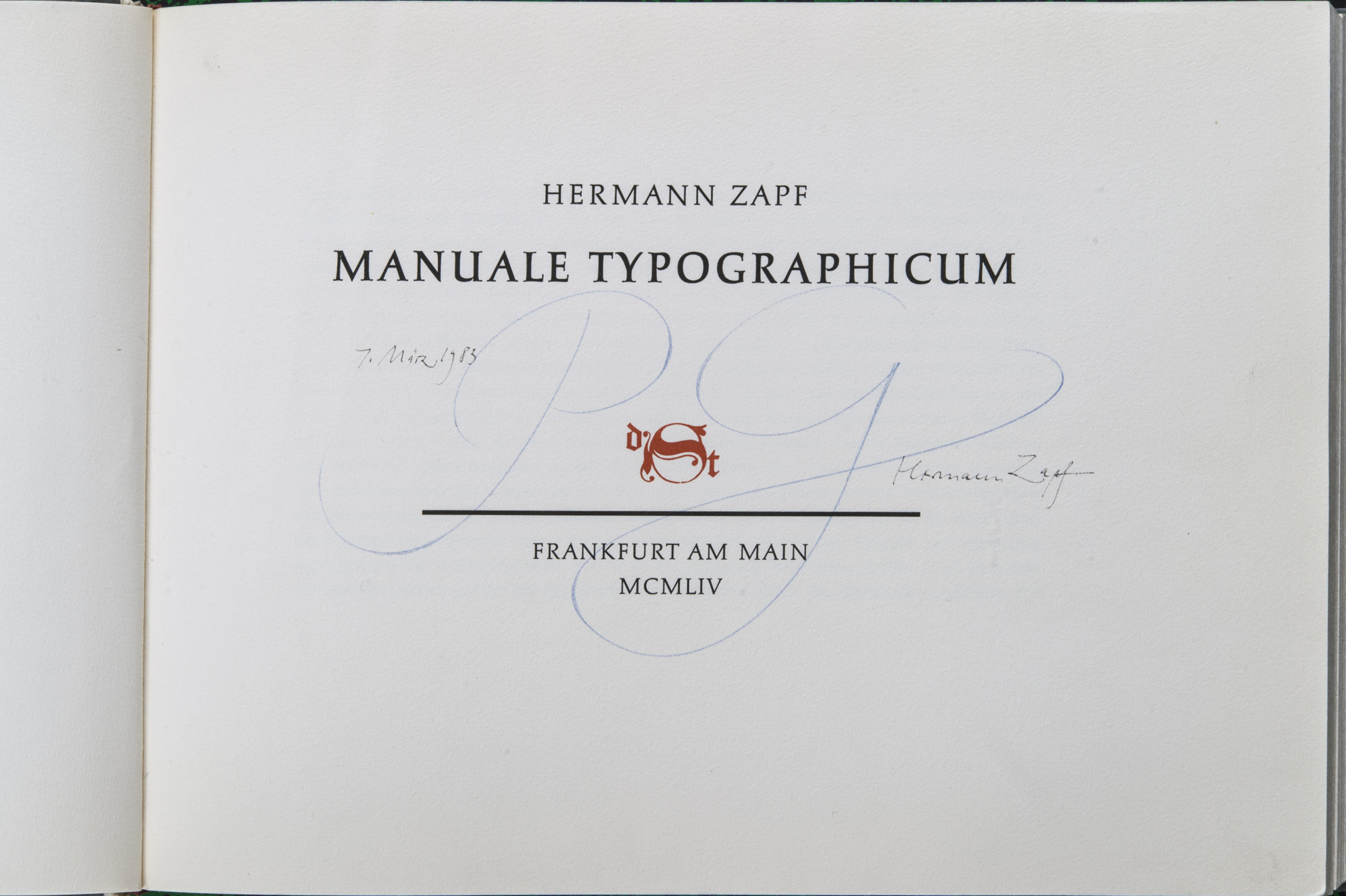
Hermann Zapf vous connaissez tous
Bien sûr, vous ouvrez votre PC ou votre Mac et vous regardez dans la listes des polices dont vous disposez. Le Palatino, c’est lui, l’Optima aussi, les vignettes bien sûr qui portent son nom et il en a dessiné tant d’autres dans les années 50 de l’autre siècle, pour la fonderie Stempel devenue Linotype, puis pour International Typeface Corp, les Zapf Chancery et j’en passe. J’ai eu le bonheur de l’interviewer dans les années 80 pour mon magazine de typo. Il nous a reçu dans une demeure blanche, carrée comme posée sur le gazon près d’une forêt de Darmstadt. Très Bauhaus, de grandes pièces très hautes, qui tournaient autour d’un patio au centre de la maison. Transparences intérieur-extérieur, tapisseries médiévales au murs. Nous l’avons intérrogé sur ces créations, ses projets, ses activités pédagogiques, et sur ce qu’il pensait de la typographie publicitaire qui avait bousculé les habitudes du «labeur» chez les compositeurs. Les approches serrées? Ah, sex typography… c’est tout dire. En partant il nous a dédicacé un livre sorti de sa bibliothèque : le Manuale Typographicum. Édité par Stempel en 1954, cet ouvrage dont voici quelques pages choisies, est une oeuvre majeure, tant pour la leçon de lisibilité que par l’expérimentation typographique. Les calligrammes d’Appolinaire (amoureux de la poésie pardonnez-moi) sont à côté un gentil amusement.
Lisibilité: Hermann Zapf a du se mettre à la tâche vers la fin des années 40. Ah oui j’oubliais de vous dire un détail important, à cette époque pas de Mac, pas d’ordis, pas de postscript ni d’html. Juste du plomb de chez monsieur Gutenberg et encore sans doute, composé manuellement (parce que la Lino et la Mono se sont répandues très lentement) avec des composteurs, des casses, et des blancs qui pesaient leur poids d’antimoine. Zapf travaillait alors à l’ancienne, maquettes papier, dessins, réalisation des compos en atelier et remontage des épreuves «couchés» sur la table avec la règle, l’équerre et le T. Regardez la page suivante:
Presse magazine, pub, généraliste ou corporate (ça n’existait pas encore) tout est là. La grammaire, titre-chapô, le texte superbement composé (interlignage très spectaculaire et agréable), jusqu’à la signature qui met une touche d’élégance finale à l’article (regardez le filets gras, élégants jusqu’à l’extrême parce qu’ils ne se touchent que dans les angles). C’est moderne parce qu’il joue avec l’inversion des interlignes, serrées jusqu’à se toucher pour le titre, doublés, triplés pour le texte, on se croirait dans une page de Vogue ou du Harper’s Bazar.
Ce Manuel est une aubaine pour nous tous qui travaillons dans l’édition ou la com. Parce qu’il inventorie toute la grammaire des possibilités de mettre en page, tout en gardant comme priorité la lisibilité. La typographie d’édition a ses codes, voici une page magnifique, simple, mais qui pourraît aussi fonctionner pour les fiches cuisines de Elle. Hermann Zapf est un type-designer mais aussi un orateur hors pair. Il donnait à l’époque de l’interview des cours chaque mois au Massachusetts Institute, c’est dire qu’il savait aussi bien communiquer par la parole que par le dessin. Et cette oralité chez lui se ressent dans la logique de ses mises en page. La typographie c’est un instrument comme la musique, qui a ses codes d’emphase (les titres en caractère gras ou en gros corps), ses rythmes -les blancs et noirs- ses articulations. Pour faire simple je dirais qu’il a poussé cette langue organisée par 26 lettres dans ses derniers retranchements. Mais avec une élégance et une finesse rarement atteintes. Dans l’exemple ci-dessus le titre est en gros corps, donc pourquoi faire gras. Il nous enseigne la simplicité par ses choix radicaux. Combien de fois j’ai entendu des clients qui voulaient grossir, grossir et engraisser leur titres, à trop hurler (et on revient à cette notion d’oralité) on n’entend plus rien.
Et à feuilleter ces quelques cent pages de démonstration magistrale on s’aperçoit qu’il a touché à tous les styles, et bien avant Neville Brody il faisait du Brody.
Et si vous lui demandez de vous réaliser un Flyer pour du Rap Alternatif il vous fait ça.
On pourraît rester des heures à visionner ces (ou ses) pages. J’ai juste trouvé intéressant de mettre à dispo de mes élèves ainsi que des visiteurs du Blog une aventure graphique qui tant par sa rigueur que sa richesse expérimentale nous montre que tous les styles de composition sont possibles, à condition de respecter le lecteur dans un paysage de profusion de mots et d’images.
NB. la planche d’ouverture de cette note, est un véritable tour de force. Entièrement réalisée en composition-plomb, elle a du demander au moins 2-3 jours de travail à un ouvrier typographe (avec les nombreuses corrections en aller-retour). Essayez de réaliser cette composition aujourd’hui avec InDesign ou Quark, je vous assure que vous y passerez entre 4 à 8 heures encore, en respectant bien entendu la même exigeance de perfection.